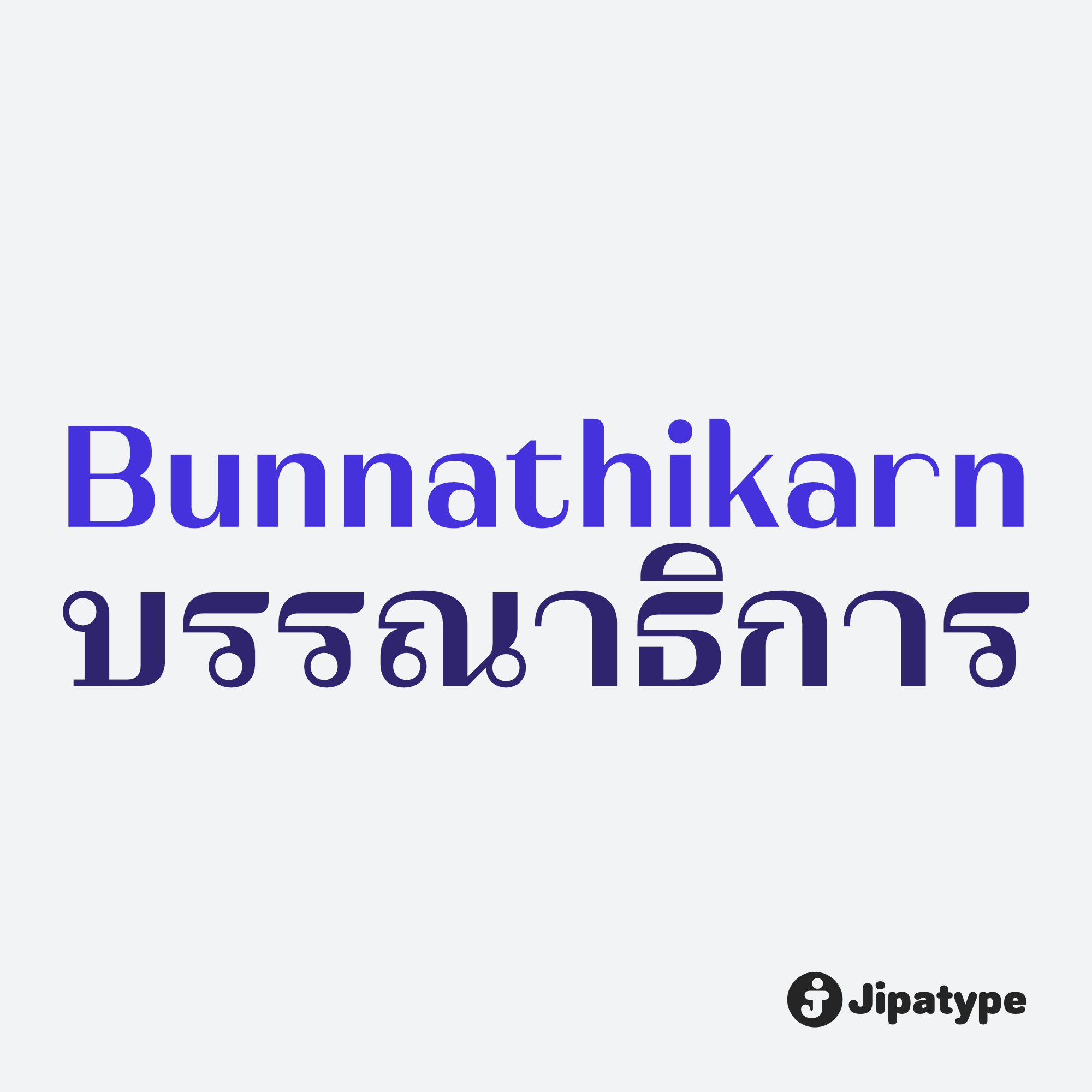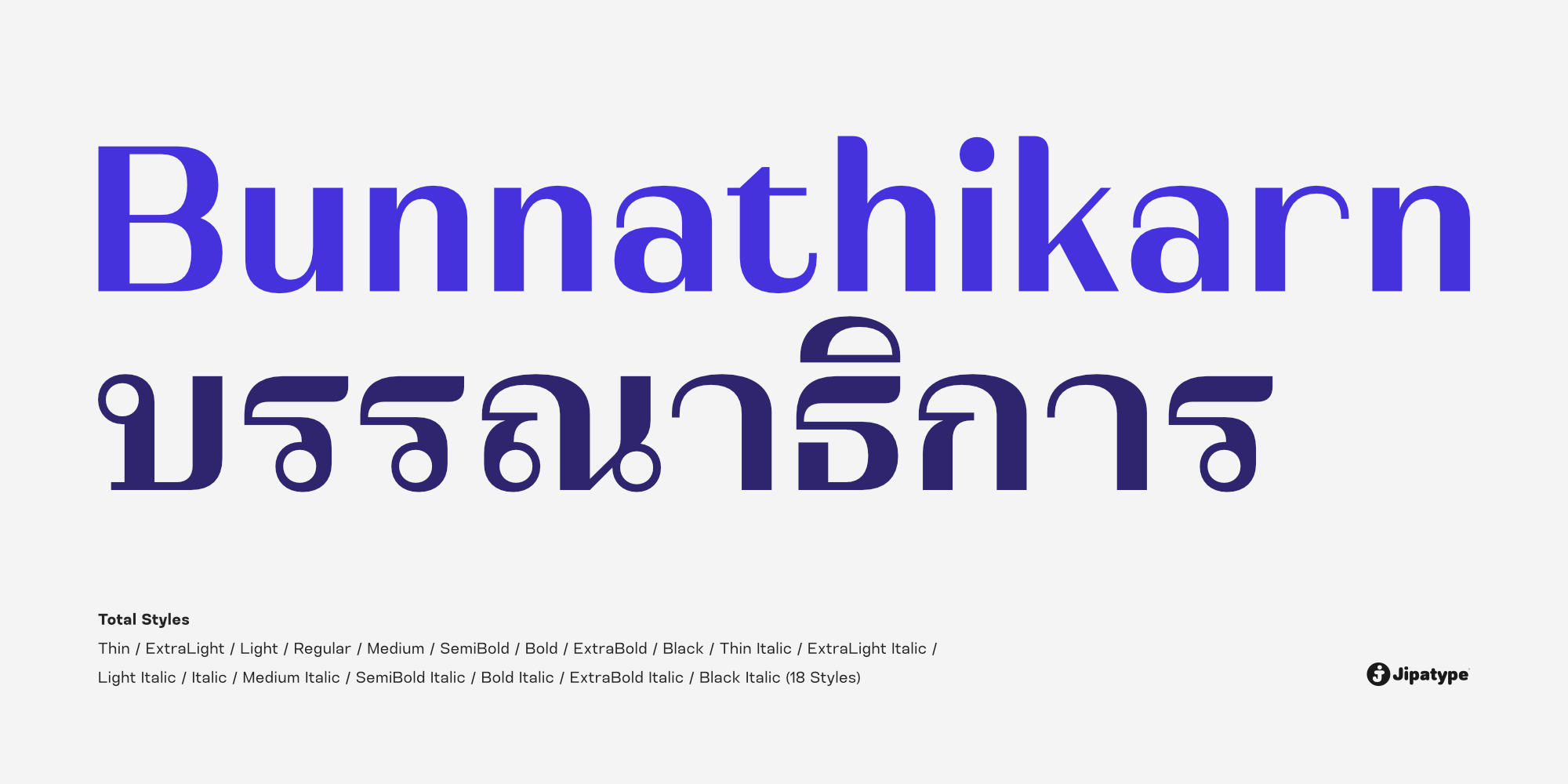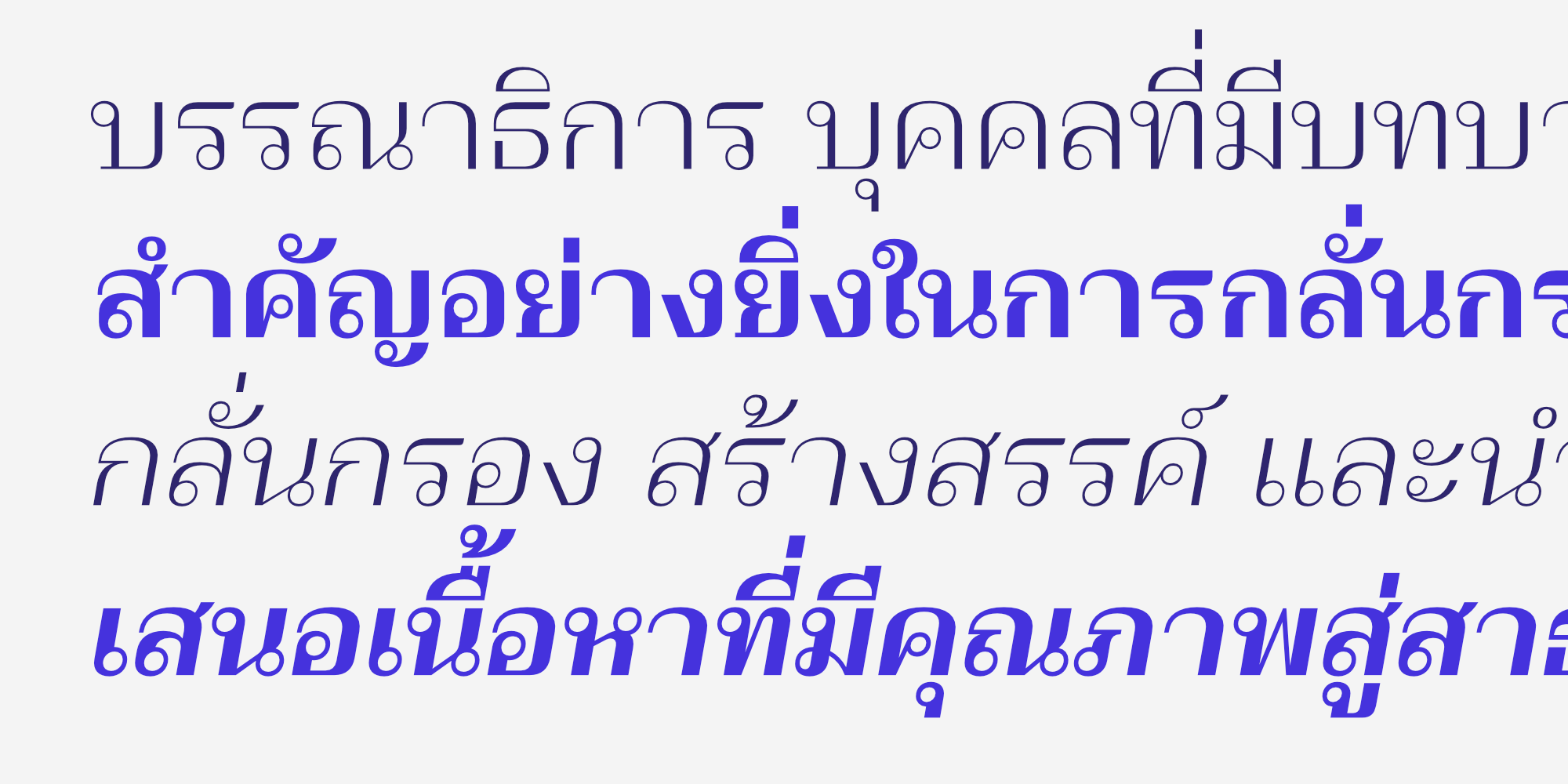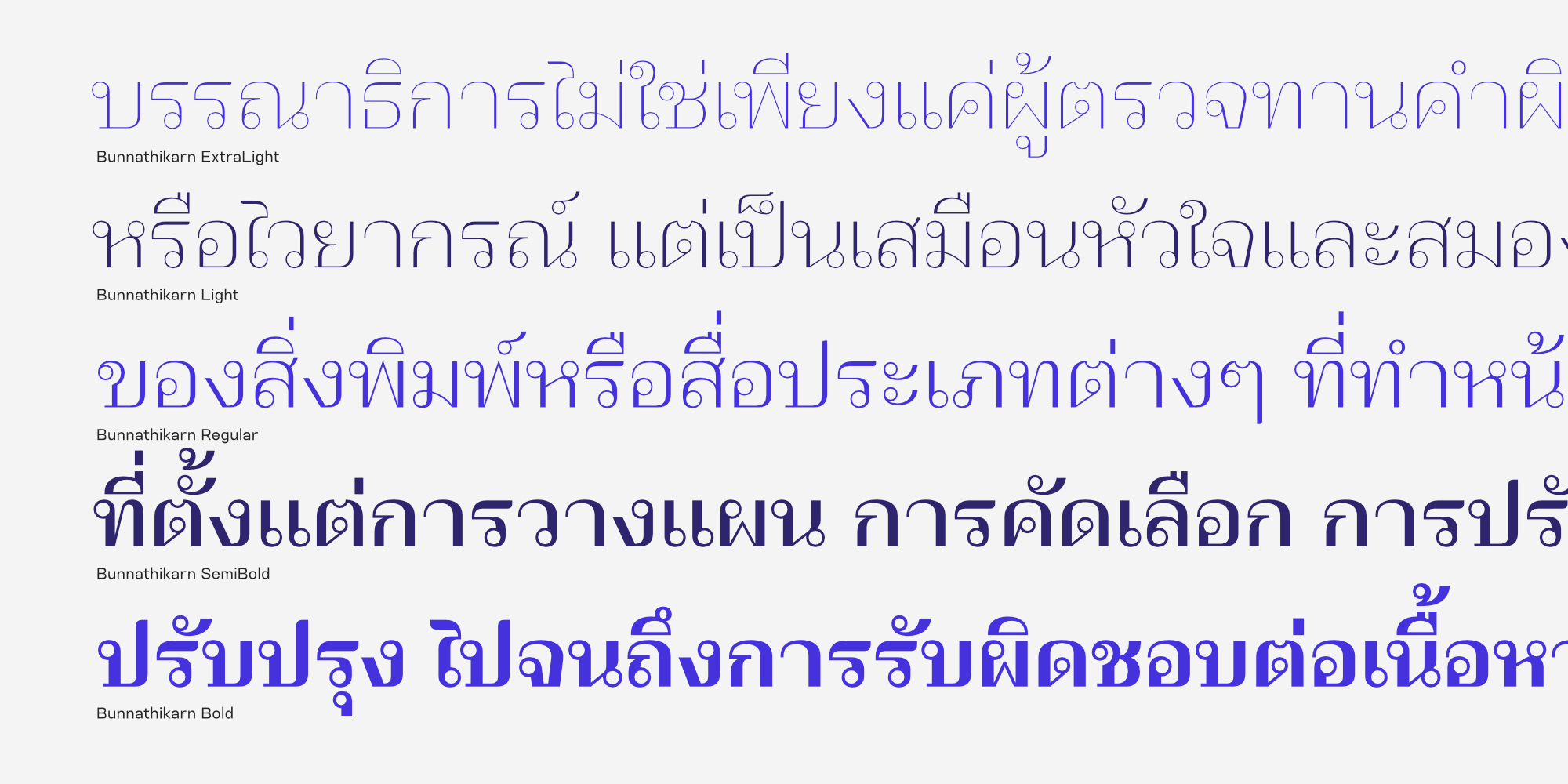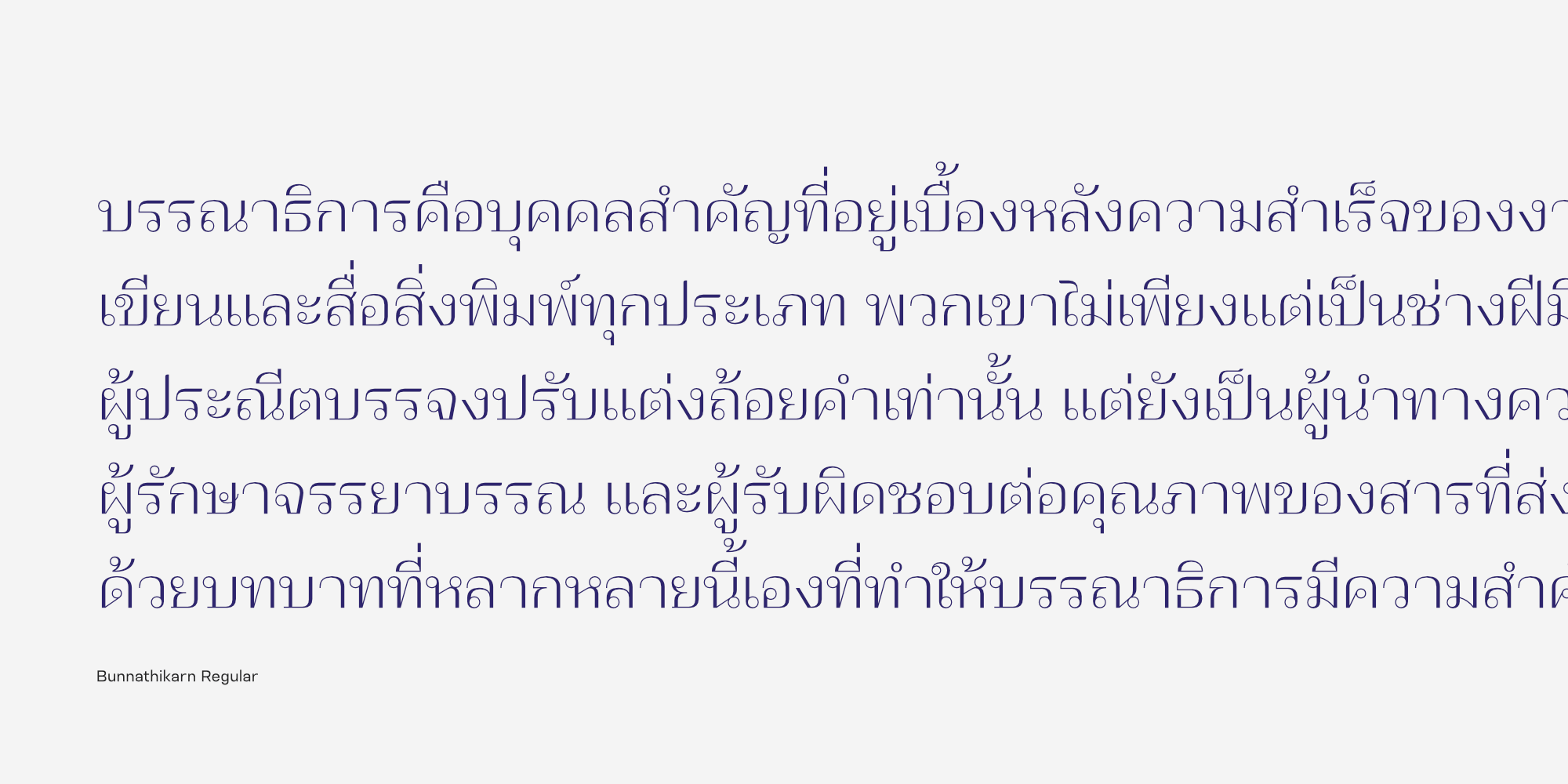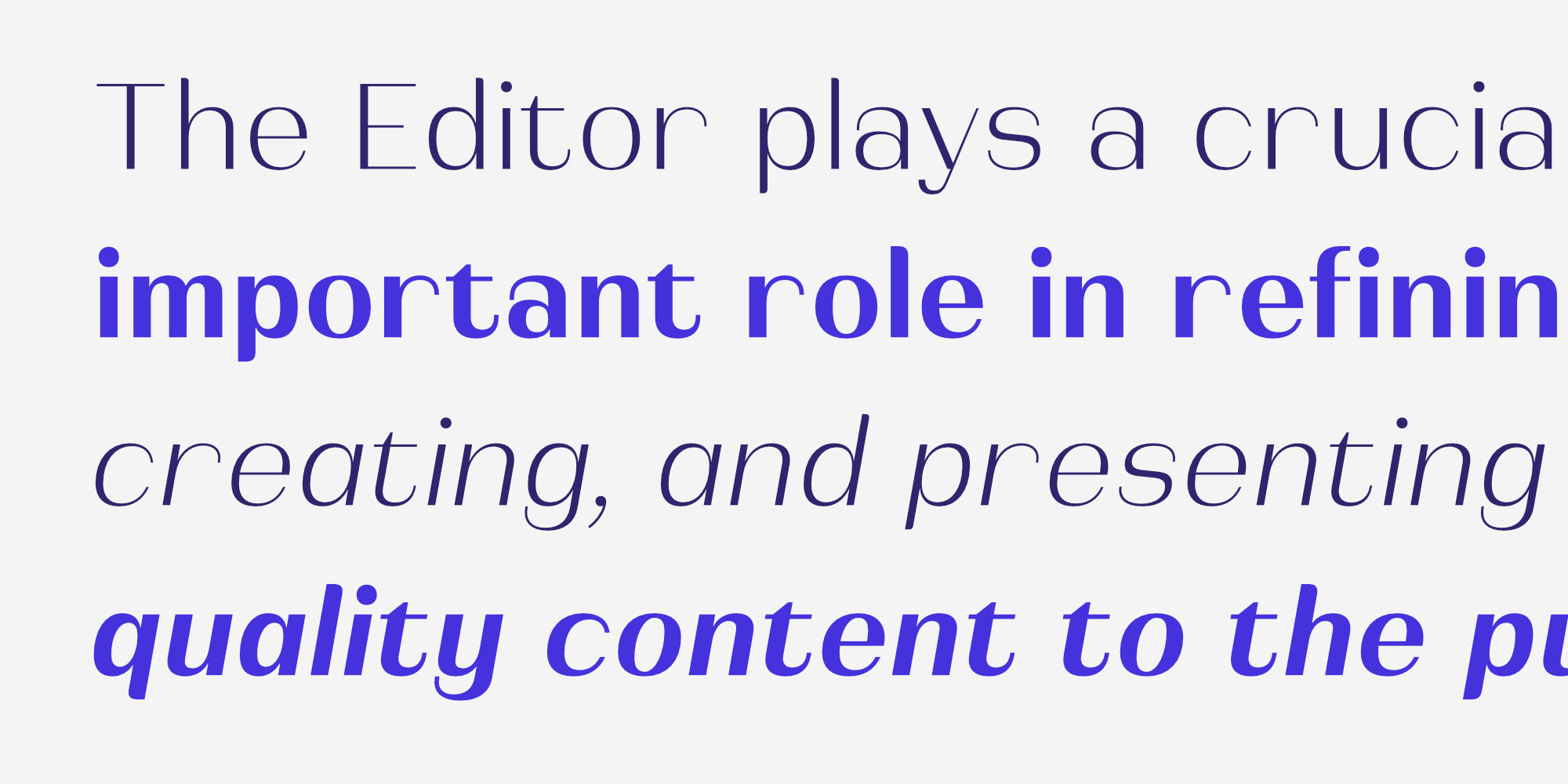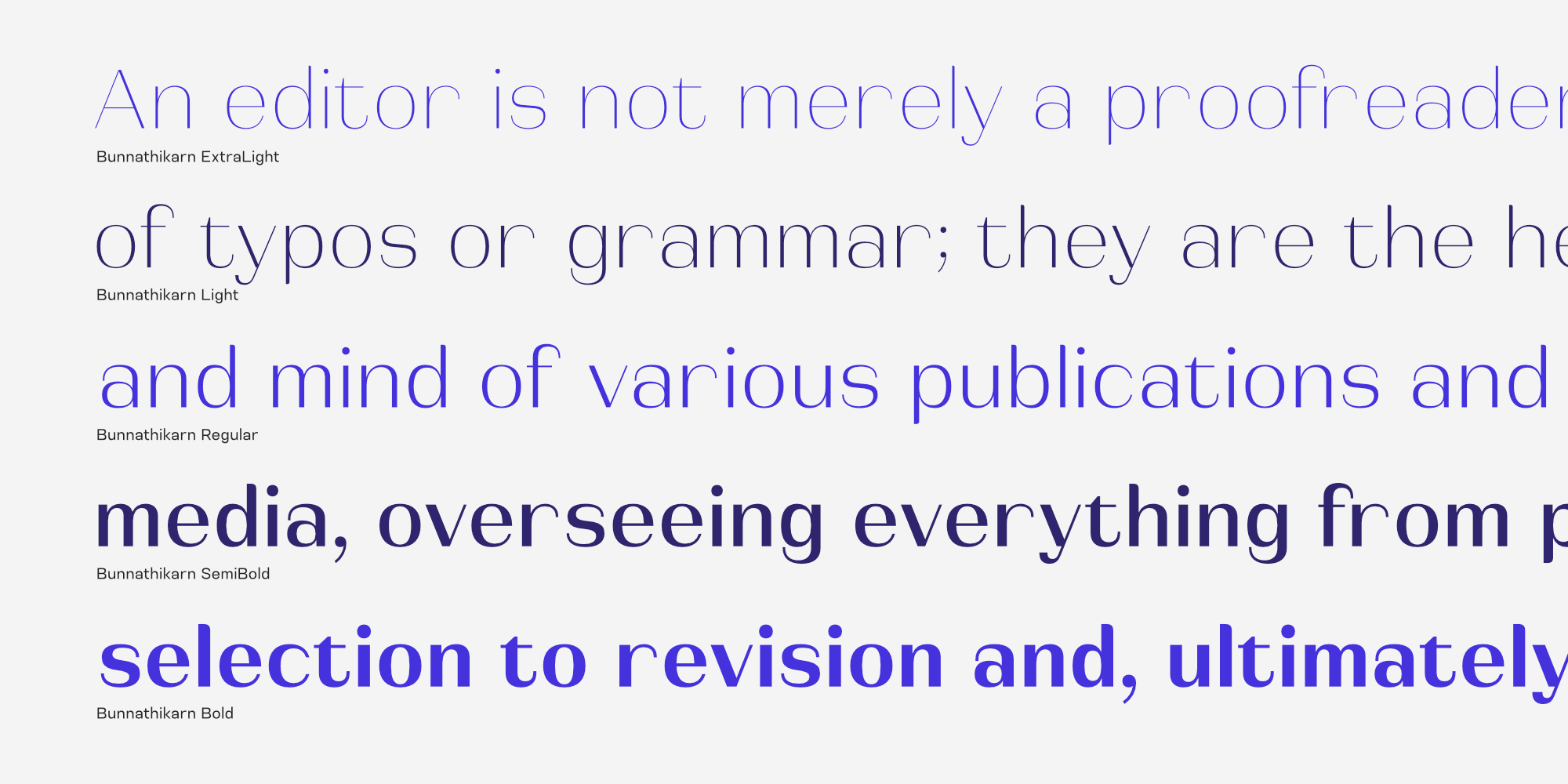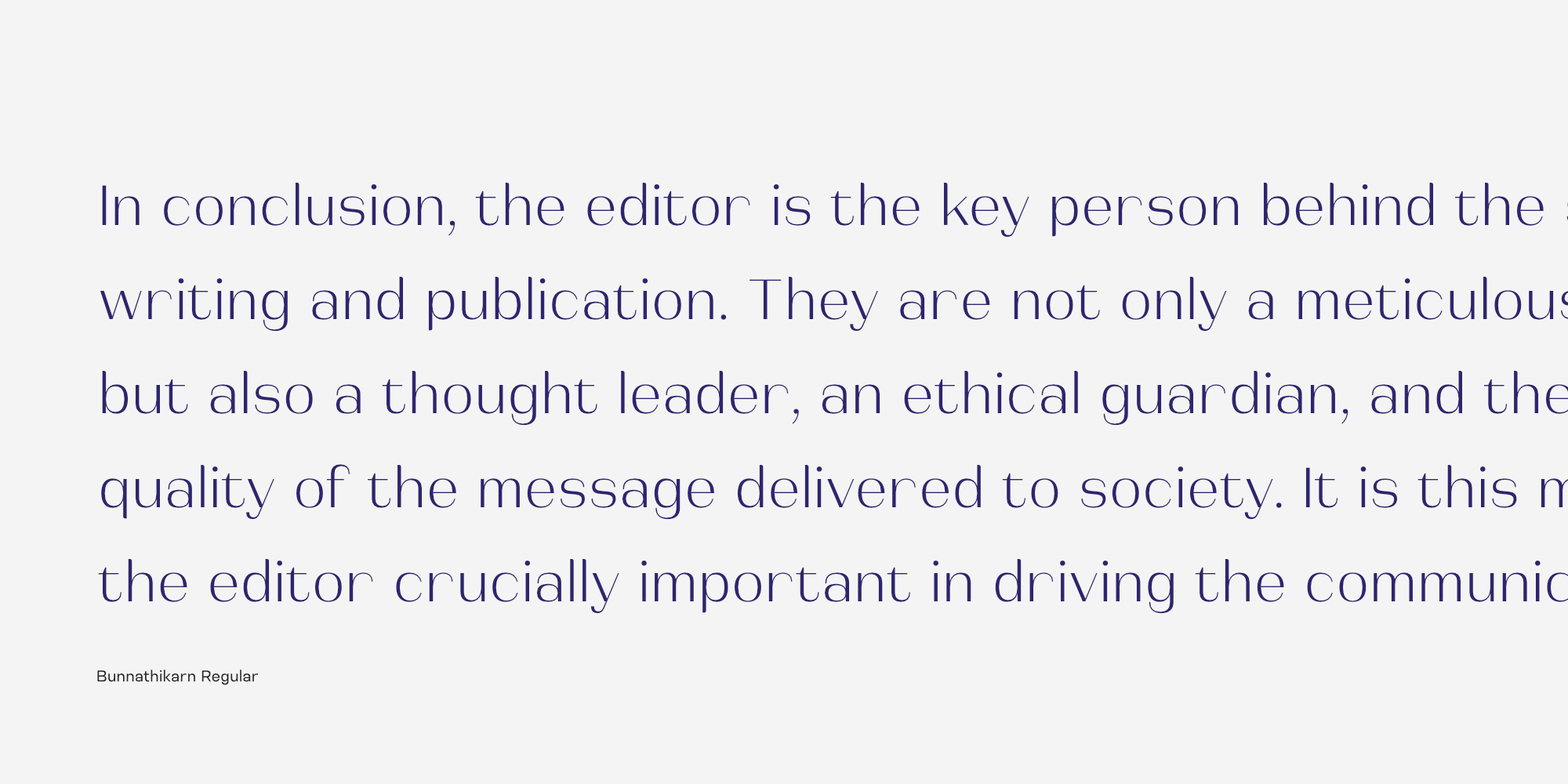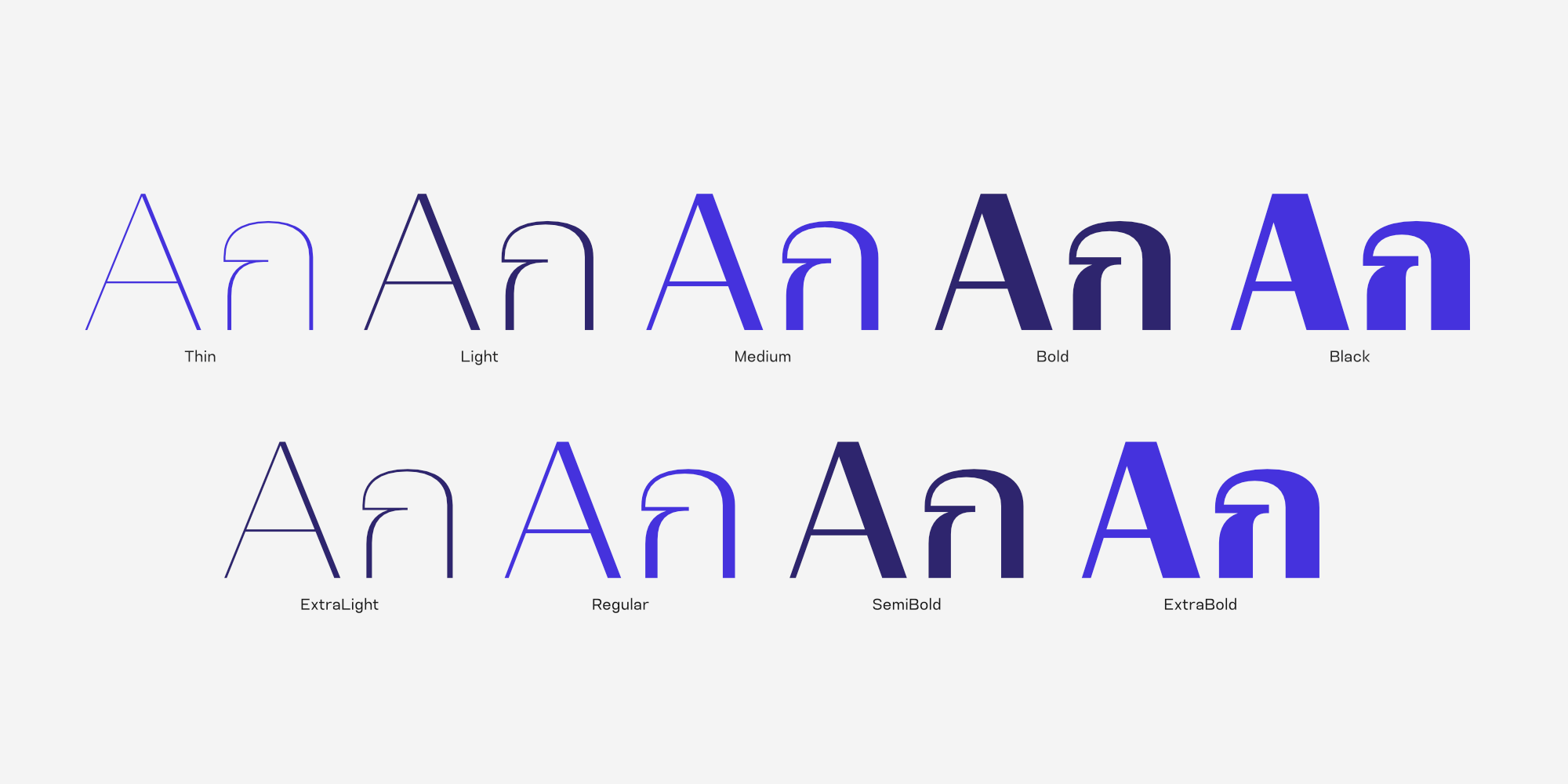
Bunnathikarn เป็นแบบอักษรแซนเซอริฟ โดยมีชุดแบบอักษรไทยเป็นประเภทมีหัว ที่ผสมผสานความคลาสสิกเข้ากับความร่วมสมัยได้อย่างลงตัว โดดเด่นด้วยเส้นสายแบบ High Contrast ที่มีการตัดกันระหว่างเส้นหนาและเส้นบางอย่างชัดเจน ให้คาแรคเตอร์ที่ดูหรูหรา สง่างาม และมีความเฉียบคม แฝงไปด้วยความน่าเชื่อถือแบบมืออาชีพ
โดยยังคงโครงสร้างที่อ่านง่าย สบายตา ครอบคลุมน้ำหนักที่หลากหลายตั้งแต่เส้นบางเบาไปจนถึงตัวหนาหนักแน่น จึงเป็นตัวเลือกที่สมบูรณ์แบบสำหรับงานออกแบบที่ต้องการเน้นภาพลักษณ์พรีเมียม ไม่ว่าจะเป็นการใช้พาดหัวนิตยสาร แบรนด์สินค้าลักชัวรี่ งานแฟชั่น ปกหนังสือ หรือสื่อสิ่งพิมพ์ระดับบรรณาธิการที่ต้องการความโดดเด่นและมีรสนิยม